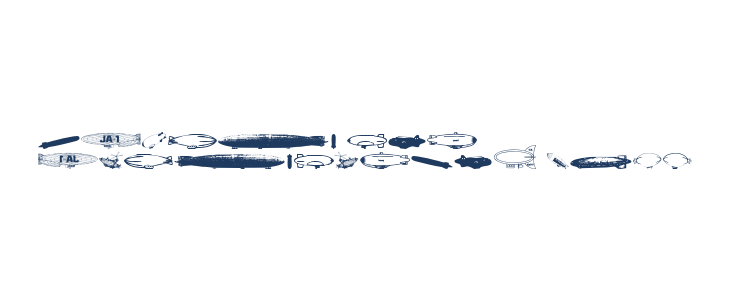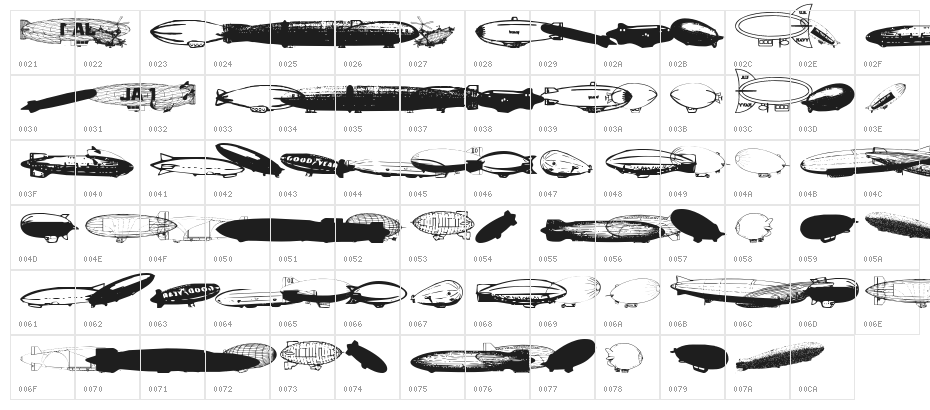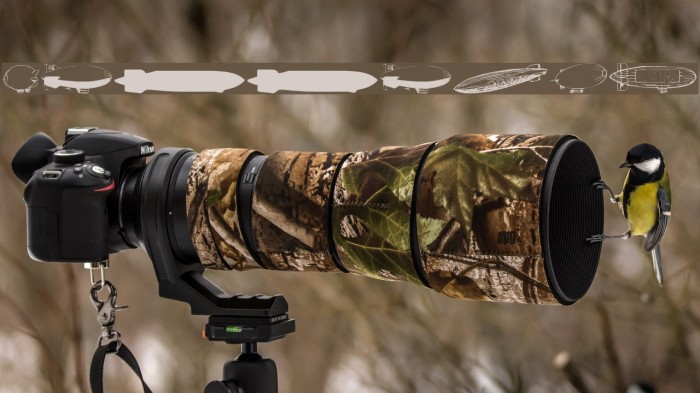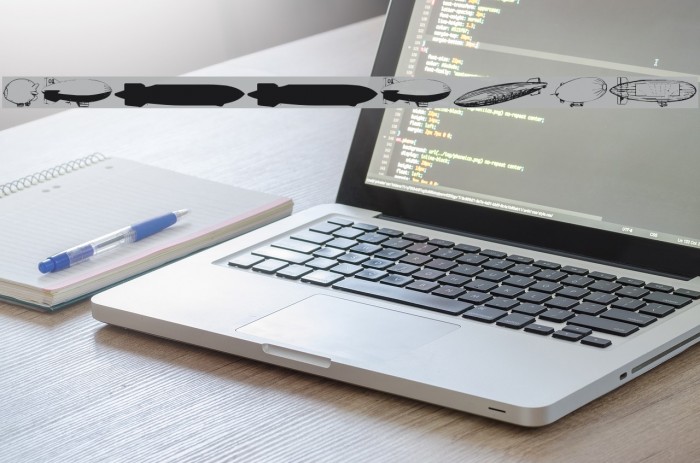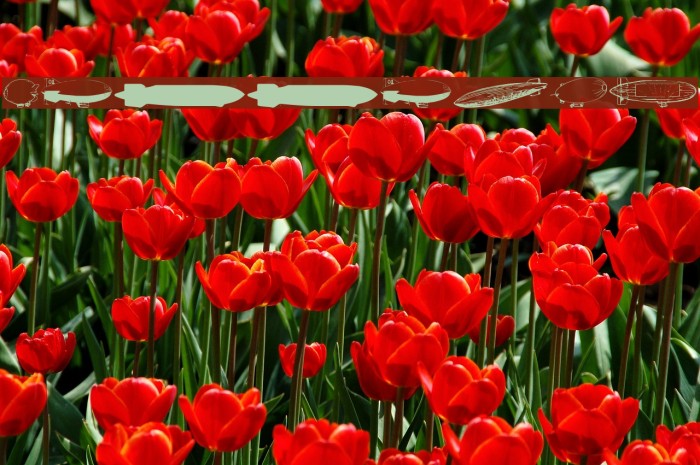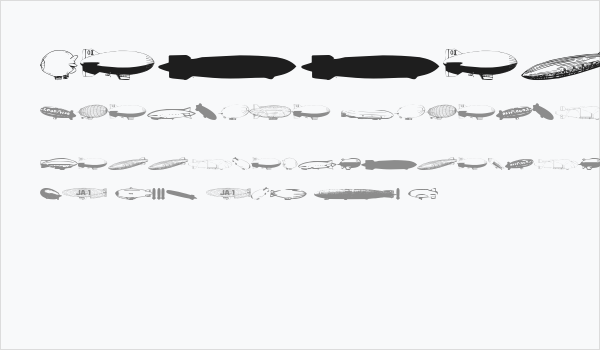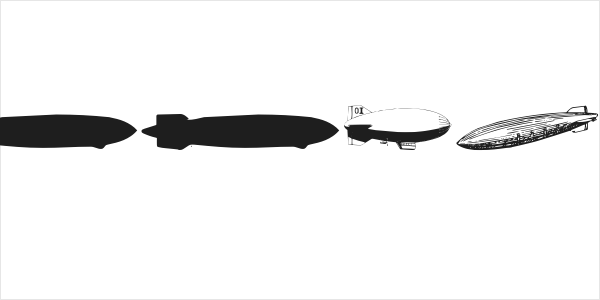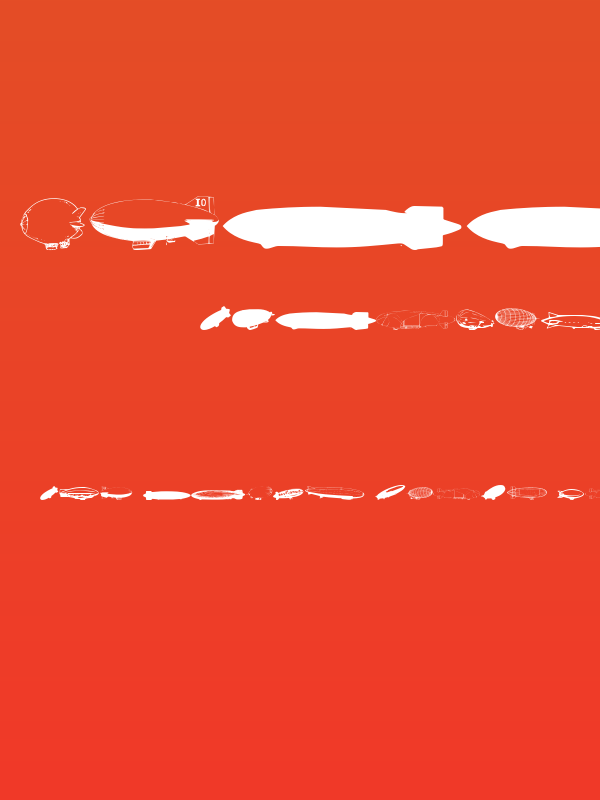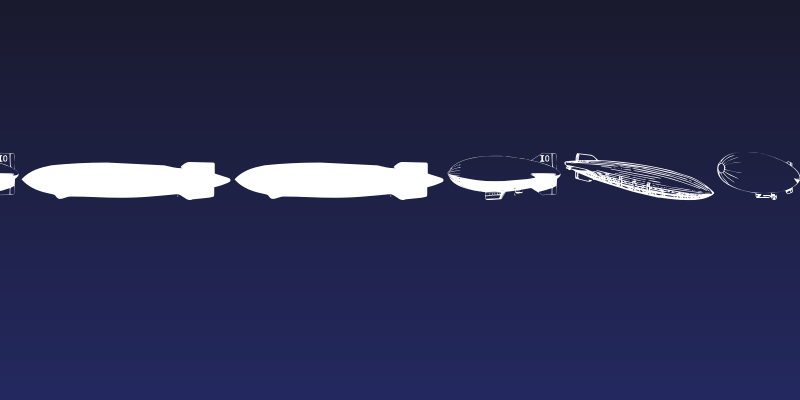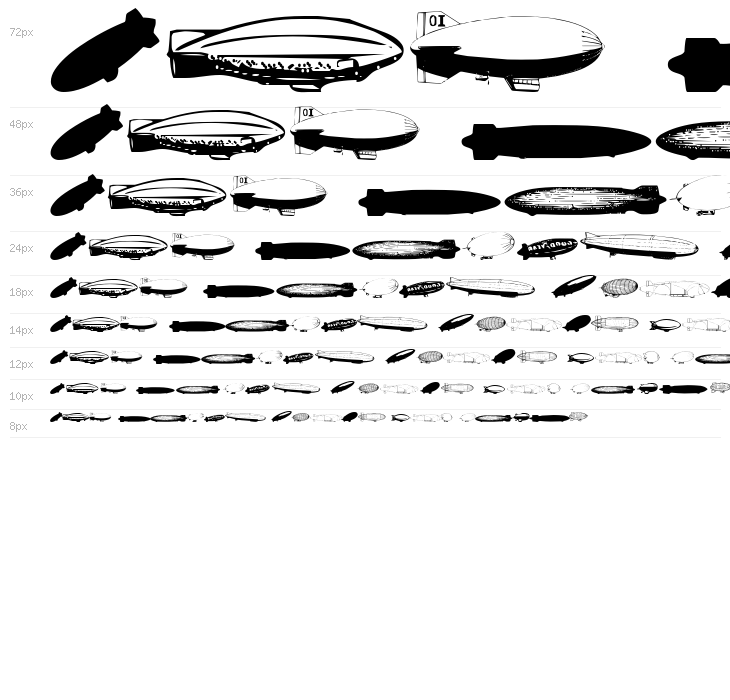
Xeppelin Font
| Gesamtstil | Decorative, Whimsical, Thematic |
| Anwendungsfall | Logos, Headlines, Posters, Themed graphics |
| Vorgeschlagene Projekte | Posters, themed event invitations, educational materials about aviation, novelty headlines, steampunk or retro-futuristic designs. |